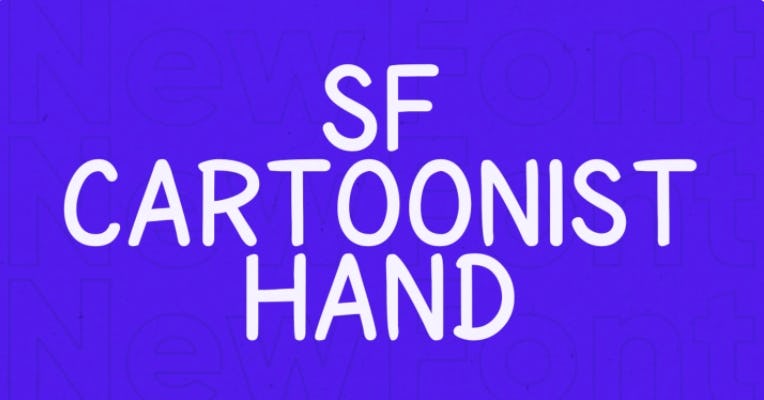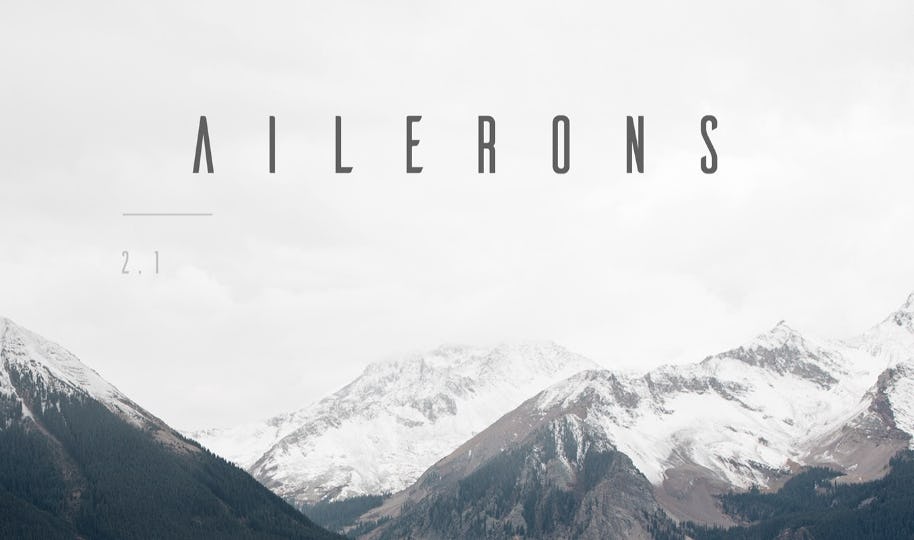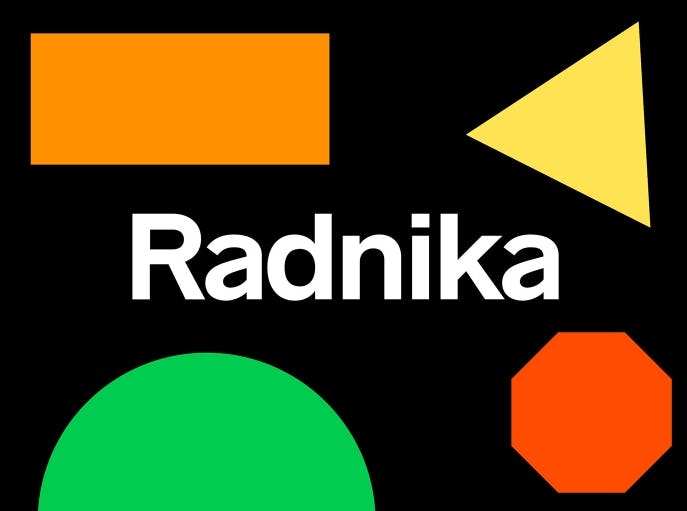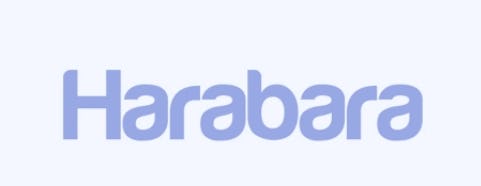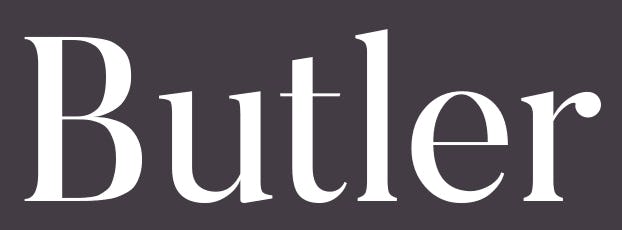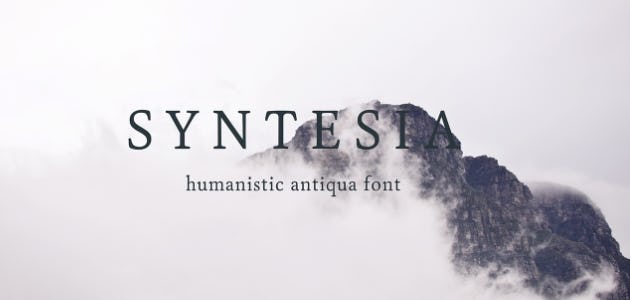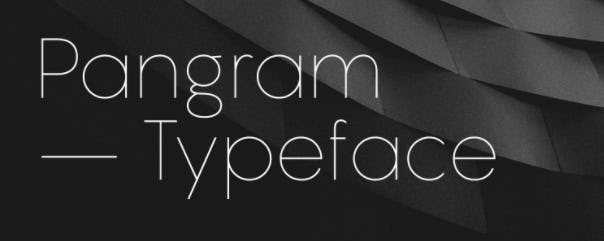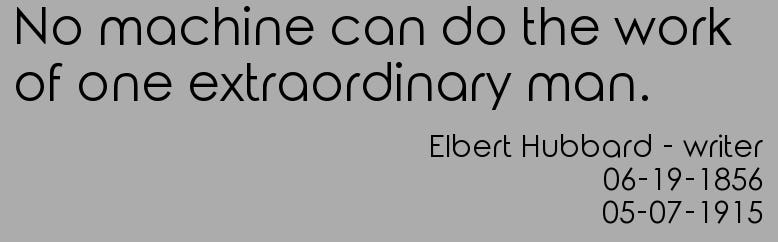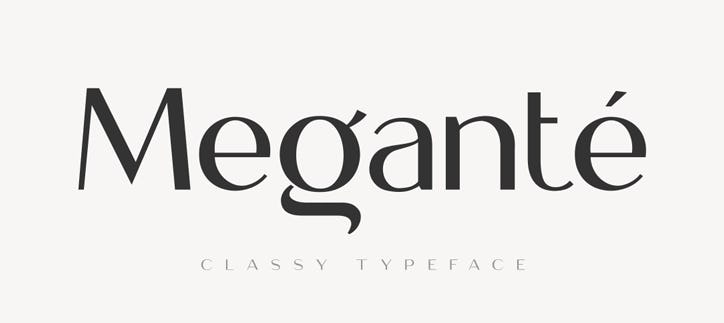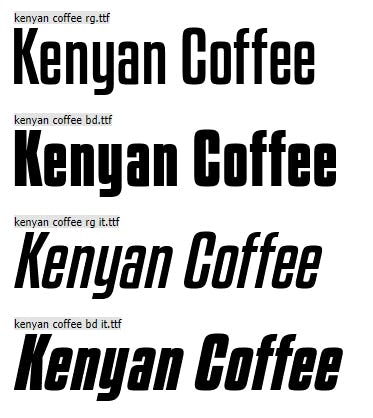
¿Estás buscando tipografías para tarjetas de presentación? Déjanos contarte un pequeño cuadro de situación al respecto.
¿Cuántas veces no has estado ordenando las cosas en tu casa y te has topado con tarjetas de presentación, recolectadas a lo largo de tu trayectoria? Unas más simpáticas que otras, desde luego, pero fíjate en la tipografía de cada una. ¿Notas algo en particular?
Las tarjetas personales son una de las primeras impresiones que se llevan nuestros contactos sobre nosotros mismos o nuestra marca, por lo cual hay que hacerlas lo más increíbles que podamos sin que pierdan la sobriedad que las caracteriza. Es por ello que hemos recopilado una lista con las mejores tipografías para tarjetas de presentación gratis, las cuales podrás descargar con tan solo un par de clics.
¿Cómo crear tarjetas de presentación memorables?
Si bien la era digital se encuentra en su máximo apogeo, aún existen algunos objetos o costumbres tradicionales que se mantienen con la utilidad de siempre. Uno de esos objetos son las tarjetas de presentación, las cuales son el método por excelencia para hacer networking y atraer clientes.
Antes de mostrarte las mejores tipografías para tarjetas de presentación, debemos aprender cómo hacerlas memorables para que nuestros contactos siempre las mantengan cerca y puedan contactarnos fácilmente.
Así que, antes de escoger las tipografías para tarjetas de visita, debemos de tener en cuenta algunos consejos. ¡Te los contamos!:
Diseño acorde a tu marca: al momento de diseñar tu tarjeta de presentación debes tener en cuenta que los colores, así como los recursos que utilices, deben guardar relación con tu marca personal. Evita los colores muy brillantes para que no se opaque la información de contacto. Hablando de colores, saber qué es la teoría del color te ayudará en este aspecto.
¡Cuidado con las medidas! Si bien ser creativo no está mal, mejor será crear una tarjeta de presentación con las medidas tradicionales (8cm x 5cm). Aunque una tarjeta con otras medidas podría diferenciarte del resto, puede que guardarlas sea más complicado, factor que te jugará en contra.
¿Y el tamaño de las letras?: este artículo trata sobre las tipografías para tarjetas de presentación, así que este es uno de los grandes puntos a considerar. Lo ideal es que las letras de la información de contacto tengan un tamaño de 7 a 8 pt. Sin embargo, ten en cuenta que todo dependerá del diseño.
Los datos necesarios: procura que en tu tarjeta de presentación pueda estar presente el nombre de tu marca, así como los datos principales de contacto (nombre y cargo, teléfono, correo electrónico). Si el espacio te lo permite, podrías incluir, por ejemplo, las redes sociales de tu marca o tu página de LinkedIn personal.
Revisa la información las veces que puedas: recuerda que las tarjetas de presentación dirán mucho no solo de ti, sino de tu marca en general, así que lo mejor es evitar cualquier tipo de error. Revisa muchas veces la información antes de imprimir.
¡Listo! Ya sabes los consejos que debes seguir para la creación de tarjetas de presentación, ahora viene la pregunta del millón: ¿qué tipografías para tarjetas personales debes utilizar? Para hacer más sencillo el trabajo, hemos dividido las fuentes para tarjetas de presentación en cuatro tipos principales relacionados a la profesión que tengas.
¿Cómo identificar una excelente tipografía?
¿Te consideras el diseñador gráfico más talentoso de todos? Entonces debes aprender a tomar las mejores decisiones en cuanto a las fuentes para tarjetas de presentación.
Y si no te consideras el mejor diseñador gráfico de todos, no pasa nada: igual deberías sumarte a la dinámica del aprendizaje de las mejores tipografías para tarjetas de presentación, ya que esa habilidad de reconocimiento puede marcar la diferencia entre un trabajo mediocre y un muy buen encargo.
Y cómo queremos hacer lo posible para que alcances el mayor de los éxitos, te enseñaremos la mejor forma de entrenar ese ojo clínico y en qué detalles debes fijarte en cuanto a las letras para tarjetas de presentación.
Debes tener varios aspectos presentes, pero lo principal es que te fijes en lo más importante: los principales tipos de fuentes para tarjetas de presentación.
1. Fuentes principales
Si hay algo en esta vida que abunda son las fuentes (no, no las de las plazas, sino las fuentes tipográficas). Estamos en una época donde existe tal magnitud de fuentes que se hace necesario buscar una forma de ordenarlas en un sólo lugar y optar por la mejor opción.
¿Y cómo podemos hacer esto? No es como si quisiéramos agrupar la arena de un desierto: hay numerosas fuentes tipográficas pero cada una está definida con un estilo particular, por lo que te mostraremos un pequeño truco para poder elegir la correcta para tu proyecto: categorizándolas (es decir, dividelas por categorías simples).